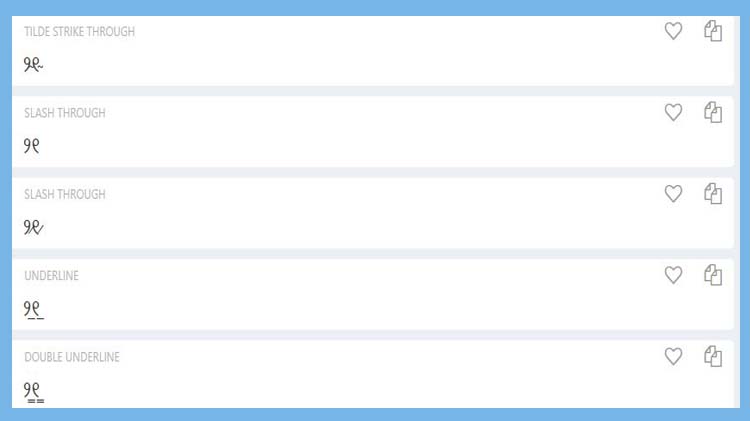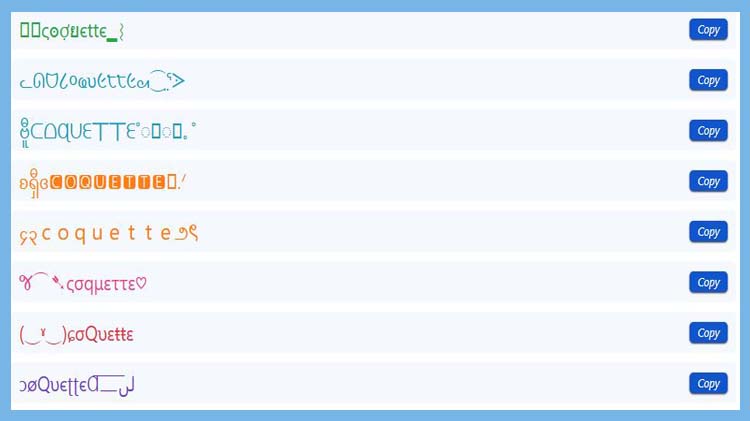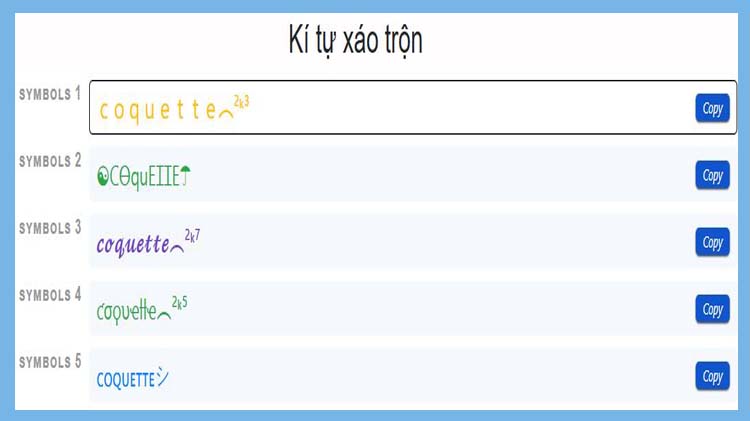
Tuyển tập bộ Kí tự coquette đặc trưng, có màu sắc, đẹp và sáng tạo nhất 2025
Kí tự coquette là các biểu tượng, chữ cách điệu, hoặc emoji mang phong cách nữ tính, ngọt ngào, lãng mạn, thường gắn với thẩm mỹ Coquette và trào lưu Y2K. Chúng được sử dụng để trang trí tên, bài đăng, tin nhắn, hoặc nhật ký, tạo điểm nhấn đáng yêu và thu hút. Đặc biệt, các kí tự nơ (?, ౨ৎ, ୨୧) là biểu tượng nổi bật nhất.
Bài viết sau của Mobifonts sẽ tổng hợp đến bạn đọc các nhóm kí tự coquette mới nhất 2025 bao gồm: kí tự đặc trưng, có màu sắc, icon đẹp và sáng tạo theo phong cách coquette. Ngoài ra, bài viết cũng mang đến những giải đáp chi tiết nhất về những kí tự nơ đặc biệt này!
Kí tự coquette là một thuật ngữ không chính thức, thường được dùng để mô tả một nhóm các kí tự đặc biệt, biểu tượng và emoji mang phong cách nữ tính, duyên dáng, dễ thương, và có chút điệu đà, lả lơi hoặc tinh nghịch.
Những icon nơ xinh xắn có thể giúp tên hiển thị của bạn trở nên độc đáo hơn, thu hút sự chú ý và thể hiện phong cách cá nhân một cách tinh tế. Dưới đây là một số mẫu kí tự coquette phổ biến:
౨ৎ
ꔫ
၄၃
୨୧
𝜗𝜚
୨⊶୧
୨⋆୧
୨⨳୧
Một trong những điều thú vị về kí tự coquette là bạn có thể tìm thấy nhiều phiên bản màu sắc khác nhau như kí tự chữ nơ màu đỏ, kí tự coquette màu xanh hoặc vàng. Chi tiết những chữ nơ, icon nơ, và cái nơ đầy màu sắc sẽ giúp bạn tạo ra dấu ấn riêng biệt được tổng hợp sau đây!
Các kí tự coquette màu đỏ là sự giao thoa giữa nét duyên dáng, nữ tính của coquette với sự mạnh mẽ, đam mê và quyến rũ của màu đỏ (Theo nghiên cứu về ý nghĩa các màu sắc của Eriksen). Nó tạo ra một hình ảnh vừa ngọt ngào, lãng mạn vừa tự tin, nổi bật và có sức hút mãnh liệt. Nếu bạn muốn gây ấn tượng với phong cách này, hãy thử sử dụng các kí tự nơ màu đỏ sau:
⦏ꔫ̂⦎
꜍ꔫ꜉
░ꔫ░
〜ꔫ〜
≋ꔫ≋
ꔫ̊⫶
ꔫ҉
ꔫ̷
ꔫ̴
ꔫ̶
Theo nghiên cứu của Pantone Color Institute, màu xanh mang đến cảm giác nữ tính, dịu dàng, mơ mộng và thanh lịch. Vì vậy khi kết hợp màu xanh với kí tự coquette sẽ rất phù hợp với những ai yêu thích vẻ đẹp nhẹ nhàng, tinh tế và muốn tạo ra một không gian trực tuyến yên bình, dễ chịu nhưng vẫn giữ được nét duyên dáng.
Một số kí tự chữ nơ màu xanh theo phong cách coquette được sử dụng trên các nền tảng Facbebook, Tiktok hay Instagram như:
၄⋆၃
၄⊶၃
░၄░၃░
〜၄∿၃〜
၄♥၃
၄⨳၃
၄҉၃҉
၄၃
Kí tự coquette màu vàng mang đến một cảm giác nữ tính, vui tươi, lạc quan và ngọt ngào. Nó là sự lựa chọn lý tưởng cho những ai muốn thể hiện sự rạng rỡ, ấm áp và một chút sang trọng nhẹ nhàng, đồng thời vẫn giữ được nét duyên dáng đặc trưng của phong cách coquette. Nếu bạn muốn thể hiện tinh thần này, hãy chọn các icon nơ màu vàng này:
୨୧
୨⨳୧
୨♥୧
〜୨∿୧〜
░୨░୧░
『Ღ』
【Ღ】
░Ღ░
〜Ღ〜
Bạn muốn tìm cái nơ đẹp để trang trí tin nhắn hoặc bài viết của mình? Những kí tự sau đây sẽ giúp bạn:
꧁༒ͼáɩ•ɳơ༒꧂
ɔáɨɲơⱭ͞ ̶͞ ̶͞ ̶͞ لں͞
(‿ˠ‿)ɕáıռơ
જ⁀➴ςáίηơ♡
၄၃cáinơ౨ৎ
ᓚᘏᗢ८áɿՈơᘛ⁐̤ᕐᐷ
౨ৎɕáɨɲơ🎀
(๑﹏๑//)☪á¡ทơ
ദ്ദി ˉ͈̀꒳ˉ͈́ )✧çáìղơ
Ɔáınơ☃︎
♰C̆áĬ♰N̆ơ♰
Ϟċáıϟṅơ⚡︎
亗☾áίnơෆ
㊝CáIムNơ모
—̳͟͞͞♥ℭá¡ղơ
´꒳`ⒸáⒾⓃơ×͜×
ミ★cáιɴơ★彡
Bạn muốn phá cách hơn nữa? Icon nơ xáo trộn sẽ là lựa chọn hoàn hảo! Những kí tự sắp xếp ngẫu nhiên sẽ giúp bạn có một tên hiển thị không đụng hàng.
☯c͛⦚a͛⦚i͛⦚卍n͛⦚o͛⦚☂\
CáI卍Иơ︵²ᵏ⁴
╰‿╯໒áར卍སơ亗
⒞á⒤卍⒩ơ︵²ᵏ⁷
çáì卍ղơ︵²ᵏ⁵
Khi sử dụng kí tự coquette, có nhiều người hay thắc mắc về nó. Vậy để sử dụng kí tự này 1 cách hiệu quả hãy tham khảo 1 số câu hỏi và giải đáp dưới đây là:
Bạn có thể tạo icon nơ đặc biệt theo ý muốn của mình. Hãy thử ngay trên Mobifonts với các bước cực kỳ đơn giản sau:
Bước 1: Truy cập vào trang web Mobifonts.com bằng trình duyệt của bạn.
Bước 2: Nhập từ khóa "coquette" vào thanh tìm kiếm để khám phá hàng loạt mẫu kí tự nơ đẹp.
Bước 3: Lựa chọn phong cách yêu thích, sau đó nhấn "Sao chép".
Bước 4: Dán và sử dụng ngay trên bất kỳ nền tảng nào
Chỉ với vài thao tác đơn giản, bạn đã có ngay icon nơ đặc biệt để làm nổi bật tên hiển thị của mình!
Bạn chỉ cần sao chép các và và dán (paste) trên nền tảng mà bạn muốn sử dụng các kí tự coquette. Tuy nhiên để đảm bảo khả năng hiển thị, bạn nên ưu tiên sử dụng các ký tự Unicode phổ biến và emoji tiêu chuẩn, cẩn trọng với các kí tự kết hợp và font chữ đặc biệt và sử dụng các công cụ tạo kí tự uy tín như Mobifonts.